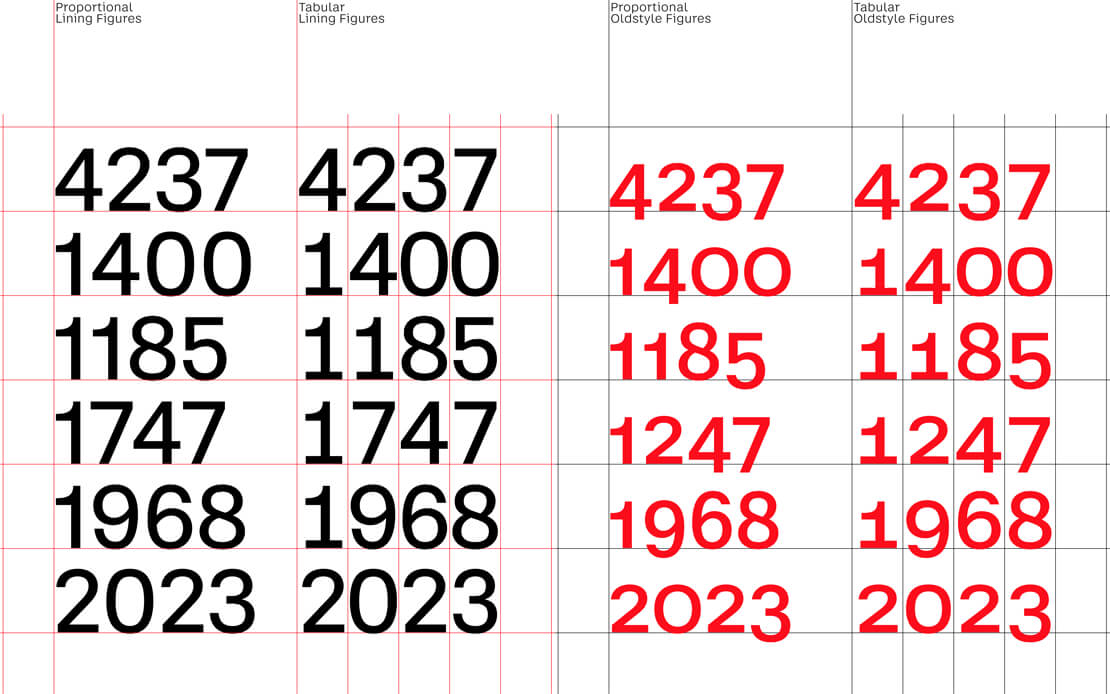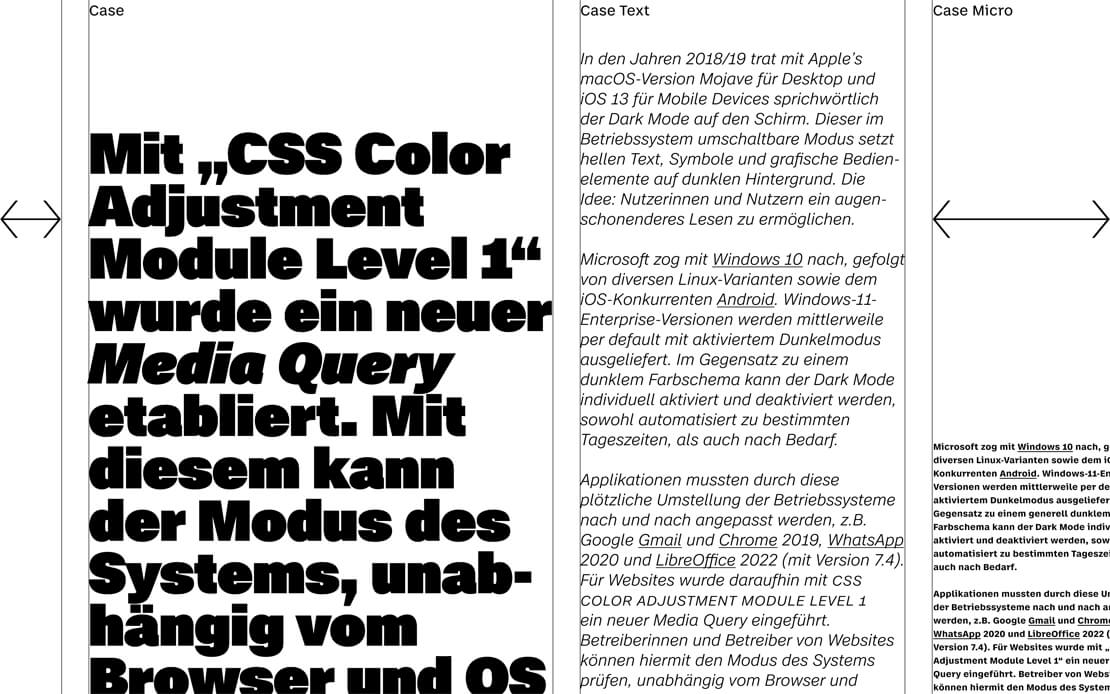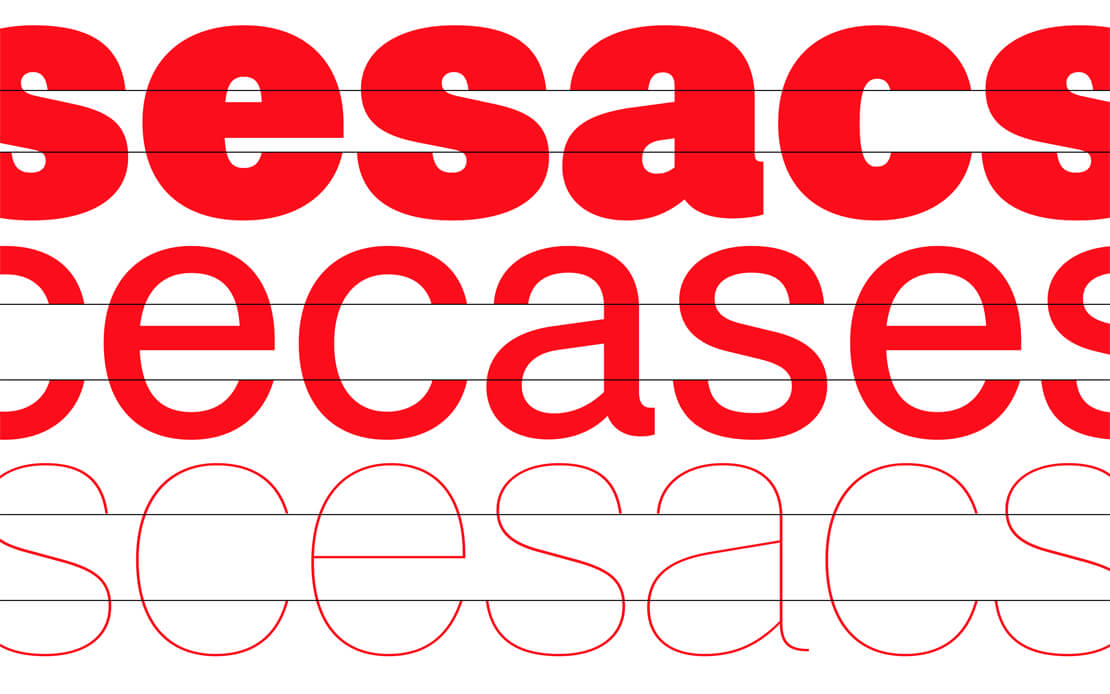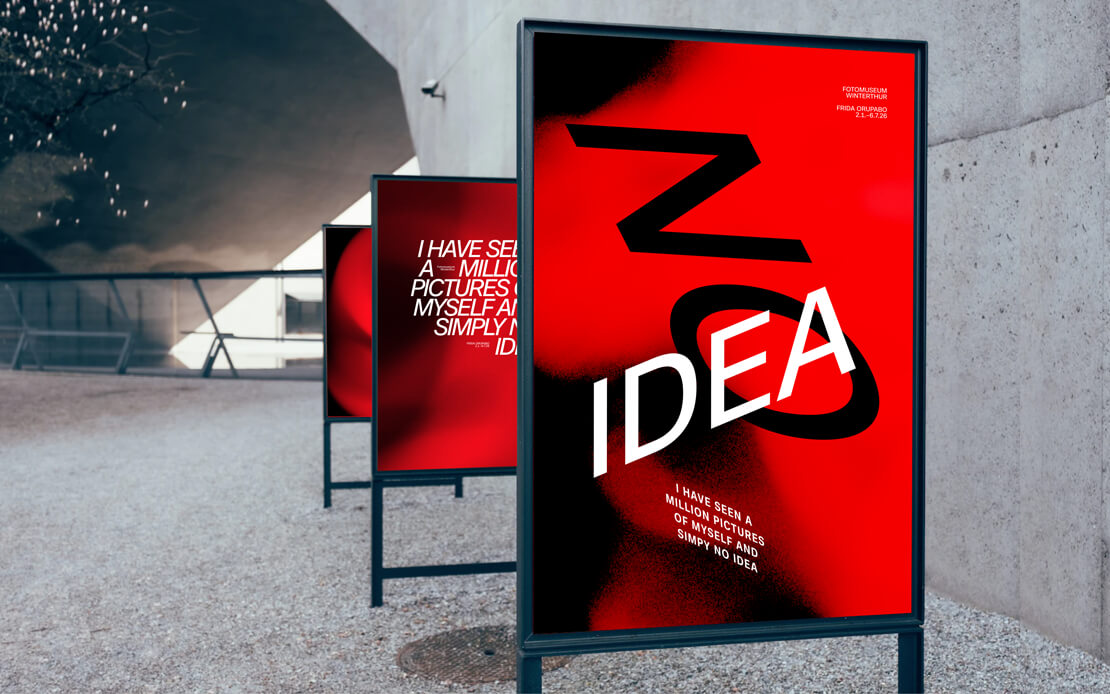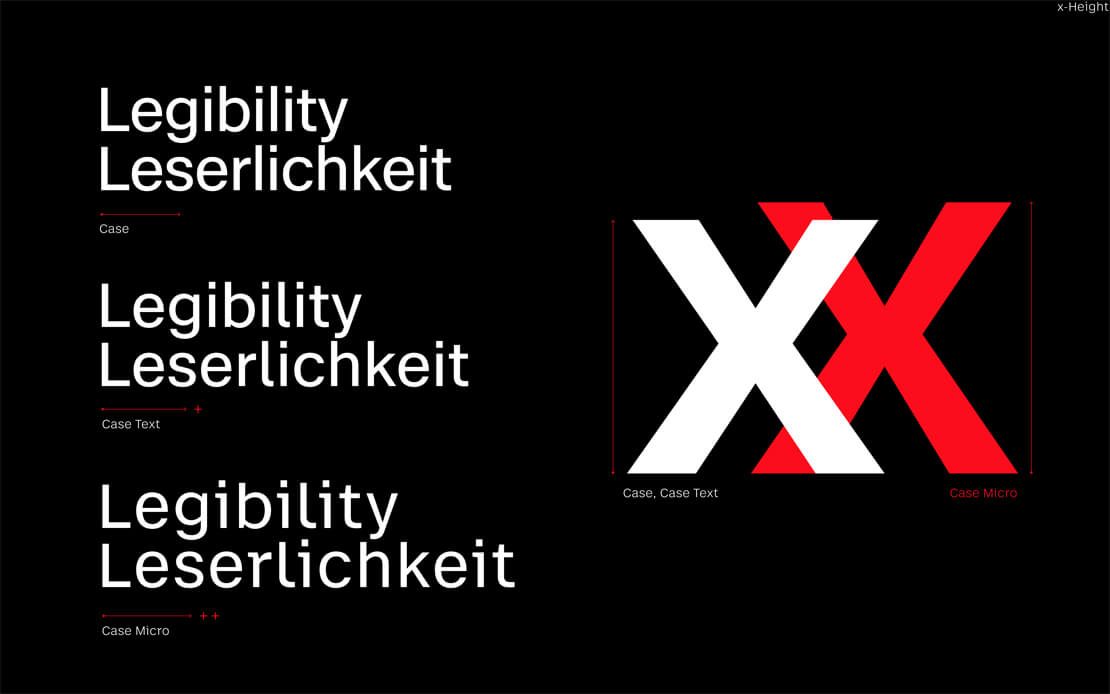
Überarbeitete Neo-Grotesk »Case 2.0«
Erik Spiekermann, Anja Meiners und Ralph du Carrois haben die Schriftfamilie »Case« von Grund auf überarbeitet. Die Anzahl der Fonts und die Zeichen wurden im Zuge des Updates verdoppelt.
Die Case-Kollektion entstand aus jahrzehntelanger Erfahrung bei der Arbeit an vielen Unternehmensschriften, bei denen die Kunden ihre eigene Version einer serifenlosen Schrift im Stil der beliebten Klassiker wollten. Nachdem die erste Version von Case im Jahr 2020 erschienen ist, gibt es jetzt eine Überarbeitung dieser sachlichen und selbstbewusst wirkenden Schriftart.
Die Version 2.0 erscheint erkennbar überarbeitet. Neben doppelt so vielen Schriften und Zeichen wurden viele Features hinzugefügt und auch die Sprachunterstützung deutlich erweitert. Insbesondere die »Text« und »Micro« wurde an den Umfang der Kernfamilie sowie die x-Höhe der »Case Text« an die der normalen »Case« angeglichen.
Die Harmonisierung umfasst außerdem feiner abgestufte Zwischengewichte. Neu sind unter anderem die Schnitte »SemiLight«, »SemiBold«, »ExtraBold« sowie die »ExtraBlack-Extrem«. Außerdem gibt es dezente Anpassungen bei bestehenden Strichstärken. Zudem sind alle Varianten über die alles umfassenden Variable-Fonts erreichbar.
»Mit einem markanten Schwerpunkt auf horizontalen Linien, bemerkenswerter Lesbarkeit, echter Kursivschrift und Unterstützung von 490 Sprachen ist Case eine moderne Alternative zu den Klassikern und kann selbstbewusst den ständig wachsenden Anforderungen komplexer Branding-Projekte gerecht werden.«, meint Ivo Gabrowitsch, Gründer der in Berlin ansässigen Typefoundry Fontwerk. »Wir freuen uns, eng mit Ralph, Anja und Erik zusammengearbeitet zu haben, um eine unkomplizierte, aber nuancierte Schriftart zu entwickeln, die Charakter und Frische in das beliebteste Schriftgenre der Welt bringt.«